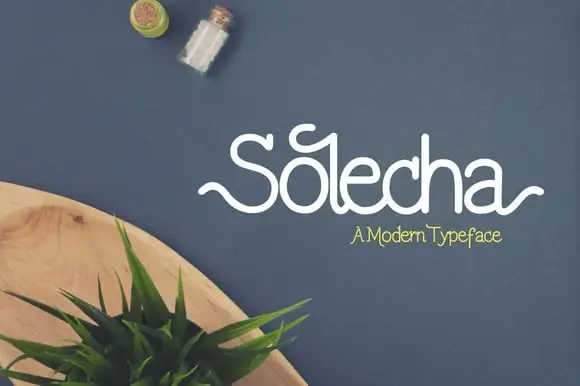
Solecha Typeface
A Solecha Typeface é uma tipografia moderna e limpa que exibe um estilo personalizável perfeito para criar cartões de convite de casamento (na inicial), headlines, logotipos e design de roupas ou materiais de uso pessoal. Suas características mais notáveis são seu formato redondo, clareza e fluidez, inspiradas em arte gráfica do clip art que flui de maneira única e distintiva. Esta fonte é uma ótima escolha para aqueles buscando um toque elegante e sofisticado sem perder a sensação vibrante característica da Solecha. Ela oferece uma combinação perfeita entre modernidade e criatividade, tornando-se o tipo de ferramenta de design imprescindível para qualquer projeto que exija estilo único. Asoleha Typeface é um recurso gráfico indispensável para designers em busca de personalizar seus trabalhos de forma inovadora.